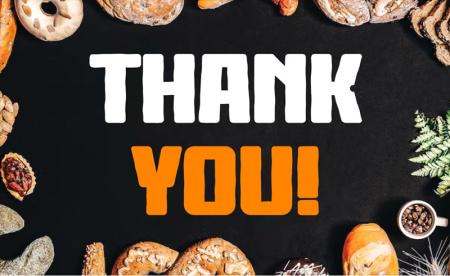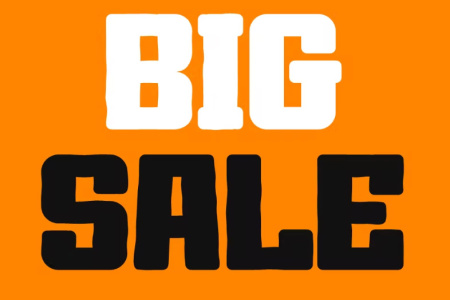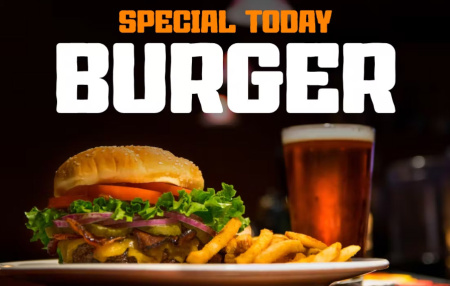
فونت انگلیسی رایگان فست فود Burger Crunchy
دانلود رایگان فونت فست فود Burger Crunchy از جی اف ایکس دانلود با طراحی زیبا و مدرن مناسب برای فست فود، برگر، منو غذا، رستوران و غیره. فونت انگلیسی فست فود یک فونت نمایشگر برجسته و معتبر است. این فونت برای هر پروژه برندسازی مانند لوگو، چاپ تی شرت، غذا و بسیاری موارد دیگر مناسب است.
✅ نام فونت انگلیسی: Burger Crunchy